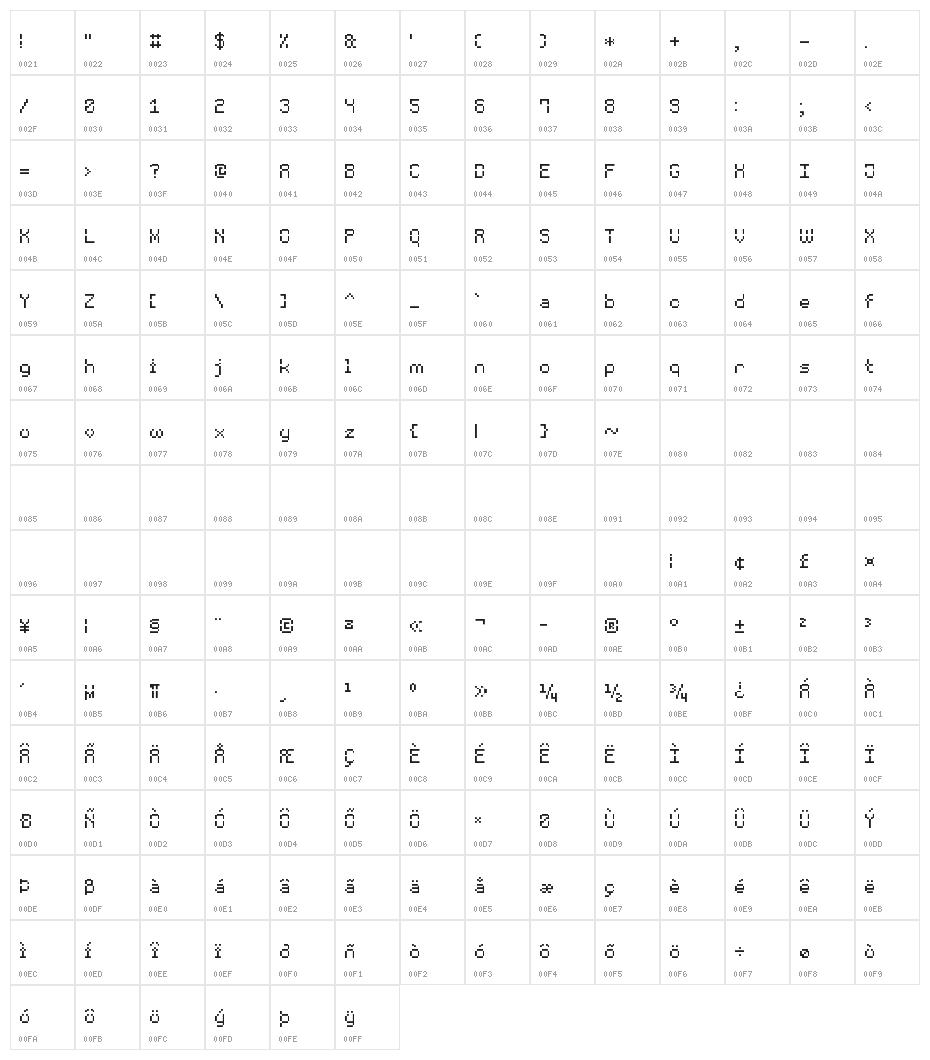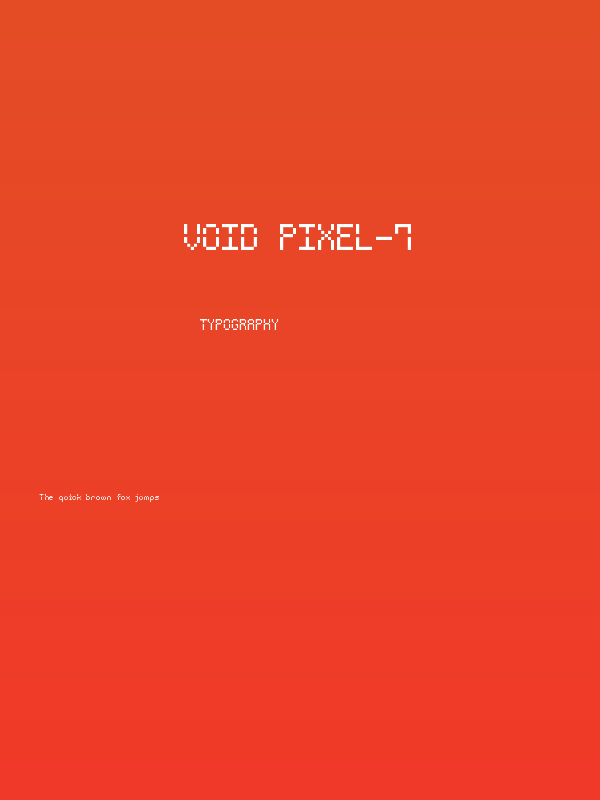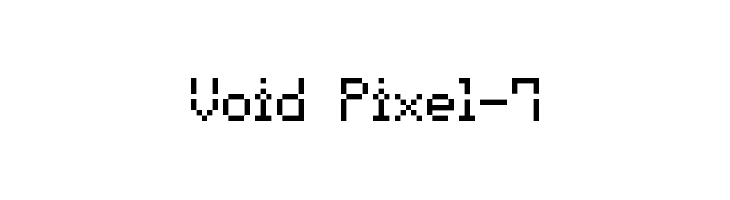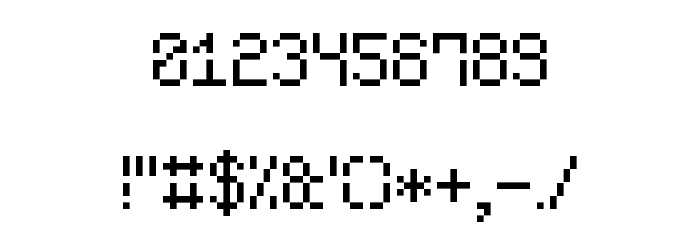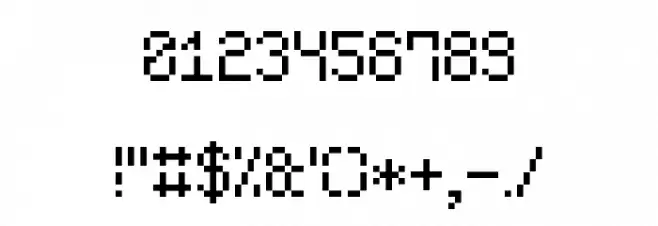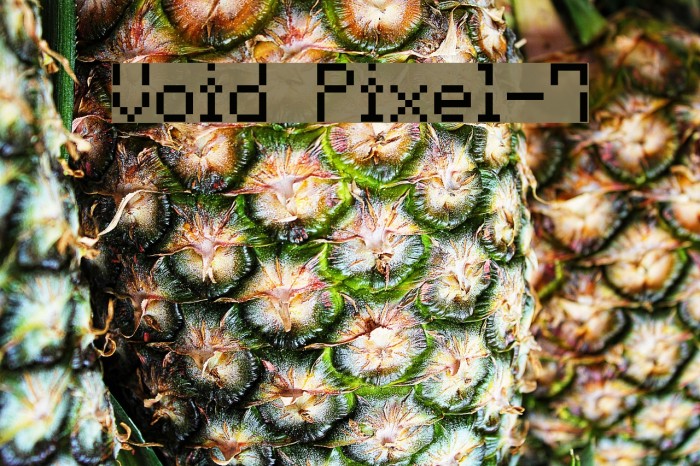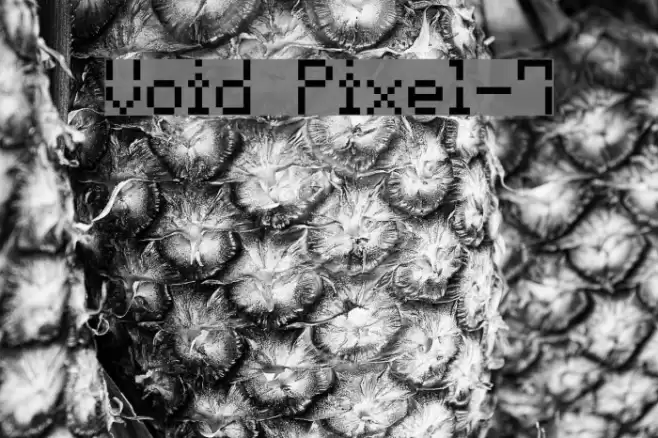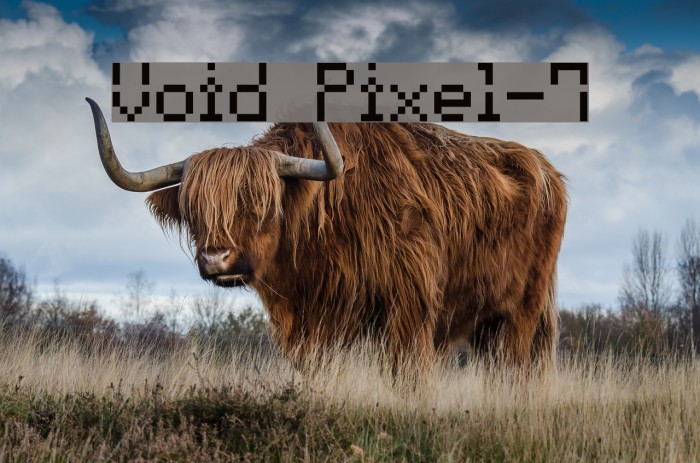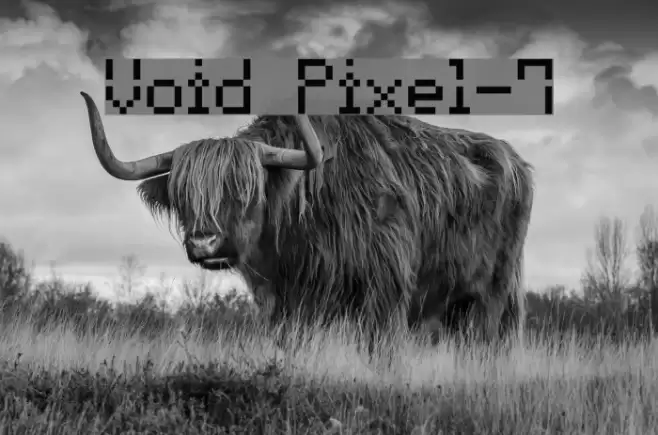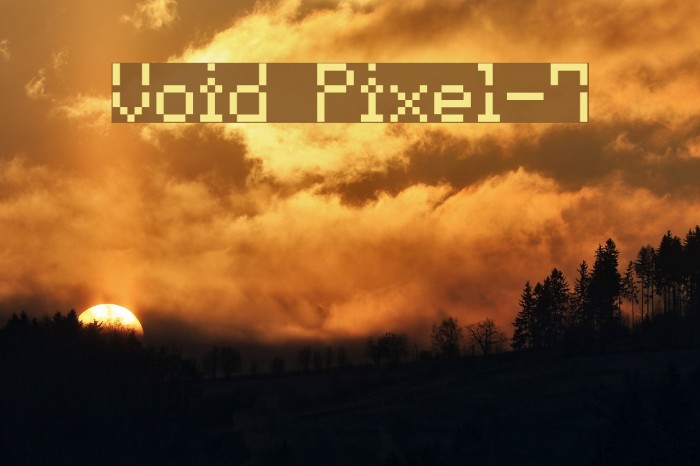
Void Pixel-7 Font
| Caso de uso | Headlines, Logos, Digital displays |
| Projetos propostos | Ideal for retro video game graphics, digital art projects, or any design requiring a nostalgic, digital aesthetic. |